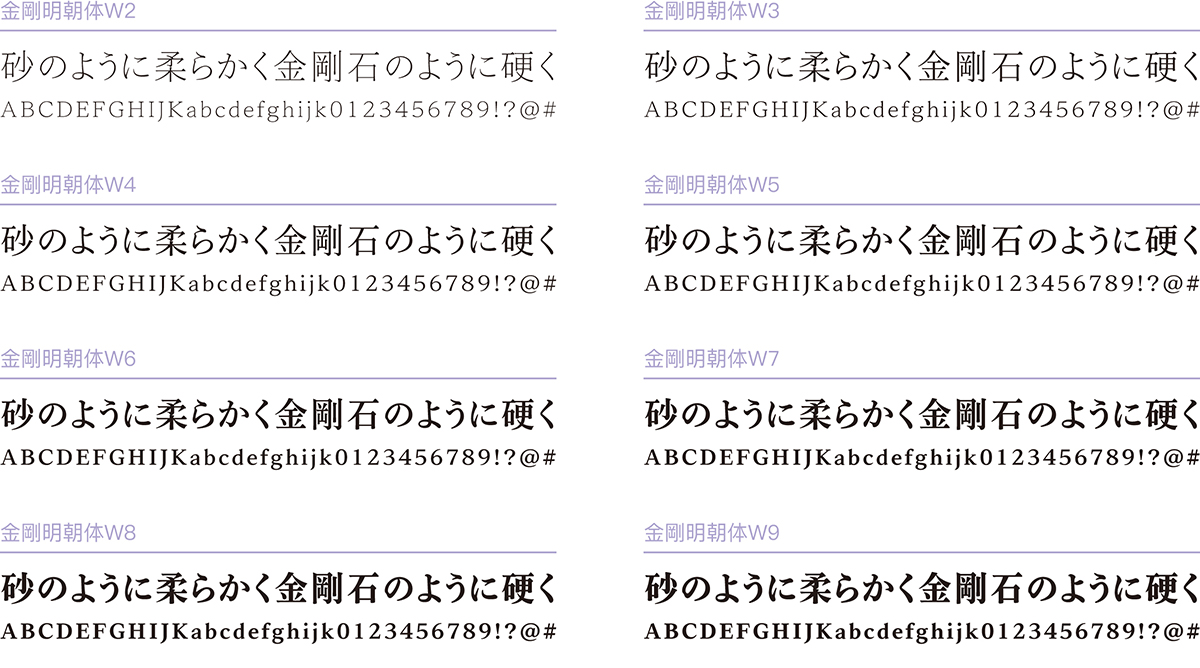
ダイナコムウェアは、ダイナフォント年間ライセンス「DynaSmart V」「DynaSmart 教育機関向けプラン」「DynaSmart 学生版」契約ユーザーに向けて、ダイナフォント30周年となる2023年という節目の年に誕生したダイナフォントの新たなる代表書体「金剛明朝体(ルビ:こんごうみんちょうたい)W2/W3/W4/W5/W6/W7/W8/W9」や、ダイナコムウェアフラッグシップフォントである「金剛黒体」のラテン語およびベトナム語の新ウエイトとして「金剛黒体 多言語【ラテン語・ベトナム語】Bold/Extrabold/Ultrabold/Black/Extrablack/Ultrablack」など、合計48書体を2023年4月18日(火)より提供したことを発表した。
その他、ゲーム作品や映像で多くの採用事例を持つ人気書体「綜藝体(ルビ:そうげいたい)W5/W7/W9」や江戸時代の芝居の看板や番付などに使用されたうねりのある手書き文字を元に開発した書体「勘亭流(ルビ:かんていりゅう)W6/W9/W11」のOpenTypeフォントStdN版や、誰にでも読みやすく配慮した美しい文字「UD明朝体(ルビ:ユーディみんちょうたい)W2/W3/W4/W5/W6/W7」のTrueTypeフォント版も追加収録されている。
【DynaSmart V2023年4月提供書体】柔剛競演によるダイナフォント2023年新明朝体「金剛明朝体(こんごうみんちょうたい)」
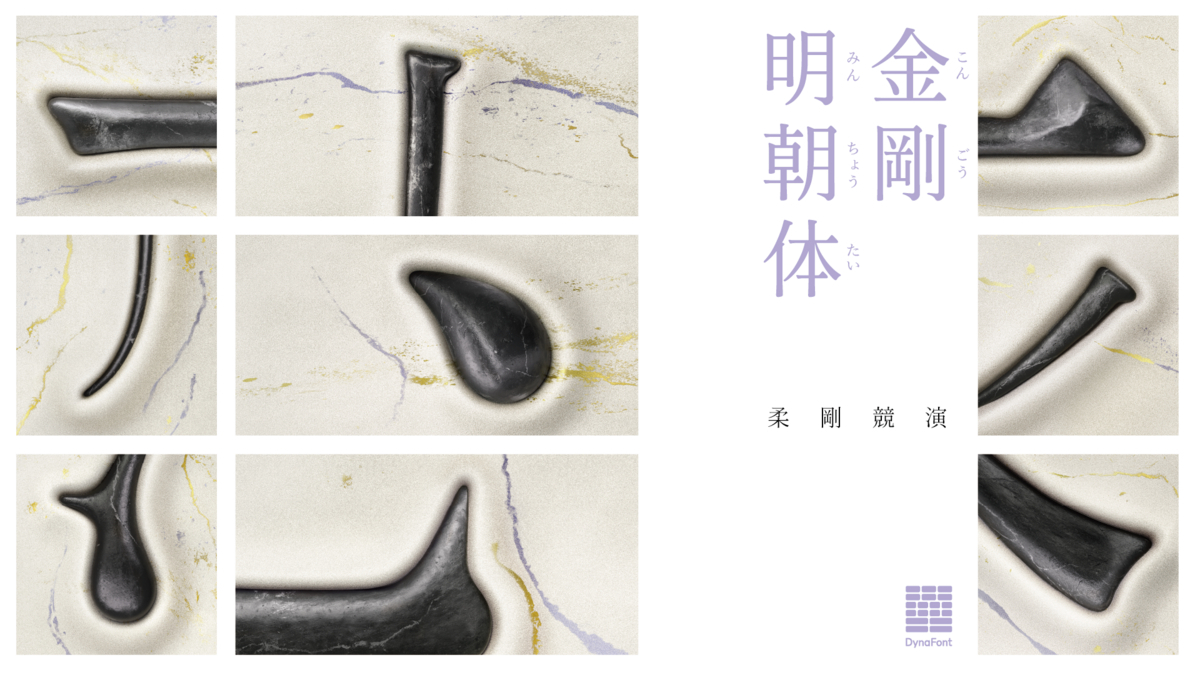
「金剛明朝体」は、彫刻の鋭敏さを和らげて書道の人間味あふれる気品を備えることで、視覚的にも温かくやさしい印象を与えた明朝体となる。
小さめなふところで古典的な雰囲気の佇まいを醸しつつも、横画を太くして角に丸みを持たせることでデジタルにおける卓越した可読性も実現した。古典的で人間味のある美しさを備えながらもデジタルデバイスにも対応しており、まさに新世代の明朝体と言えるだろう。
W2~W9までの8種類のウエイトで展開しており、キャプションから本文、見出しといった小さなサイズでの使用から大きなサイズの使用まで、様々なニーズに対応できる。
ダイヤモンドの王様と呼ばれるカーボネードのような強靭さと繊細さを保ちながらも優しい印象も備えており、紙とデジタル双方において、デザインに彩りや洗練さをもたらしている。
金剛明朝体とその他の明朝体の比較から、組み見本、活用例に至るまで、砂のように柔らかく金剛石のように硬い柔剛競演による新時代の明朝体である「金剛黒体」のその魅力を、余すところなくお伝えした特別なサイトになっている。
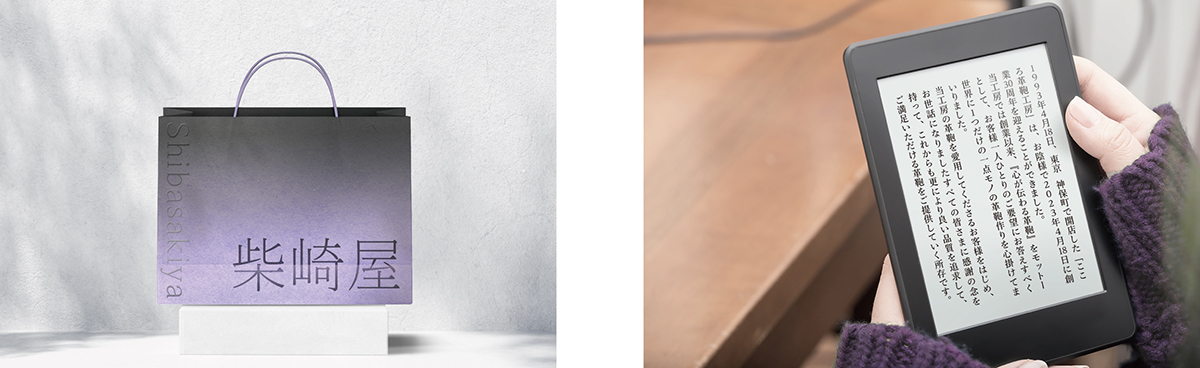
【DynaSmart V2023年4月提供書体】新6ウエイトを追加「金剛黒体 ラテン語Bold 6ウエイト」
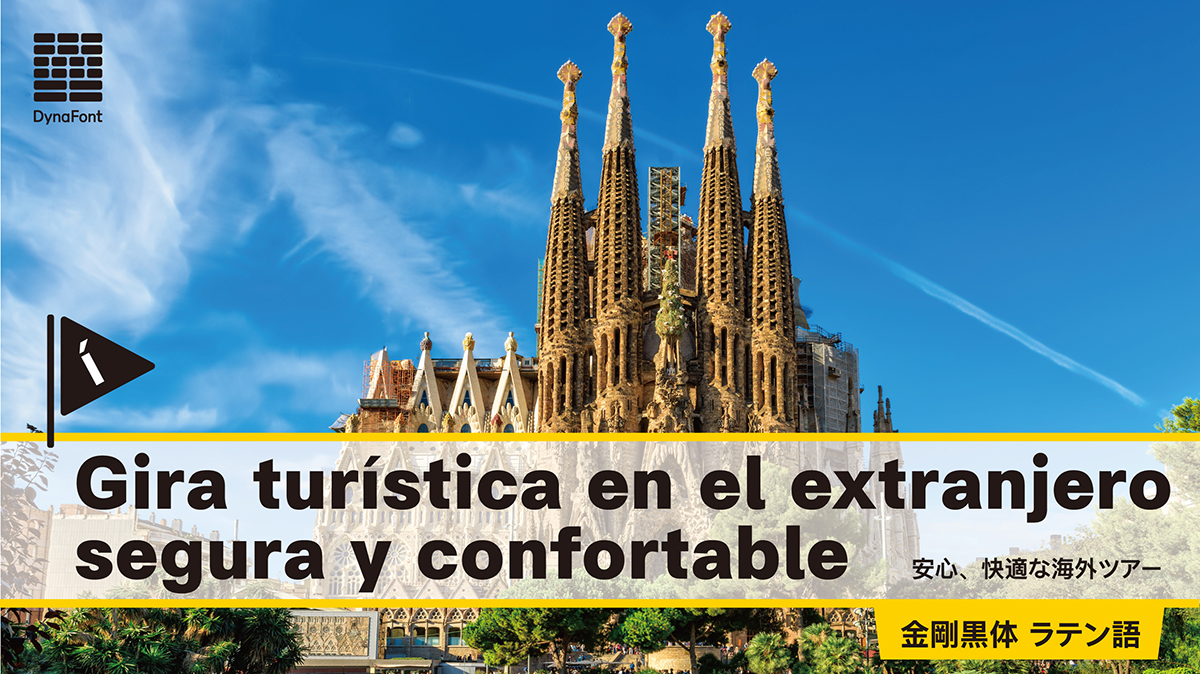
「金剛黒体 ラテン語」は、FIGS(フランス語・イタリア語、ドイツ語、スペイン語)を含むラテンアルファベット137言語の多言語書体となる。
シンプルでモダンなスタイルを軸に、全体的にすっきりと洗練されたデザインが特長。
先行リリースした6ウエイトに、それぞれの太さに合わせて最適化したBold、Extrabold、Ultrabold、Black、Extrablack、Ultrablackの6ウエイトを新たに追加して、拡充した合計12ウエイトで展開。
【DynaSmart V2023年4月提供書体】新6ウエイトを追加「金剛黒体 ベトナム語Bold 6ウエイト」
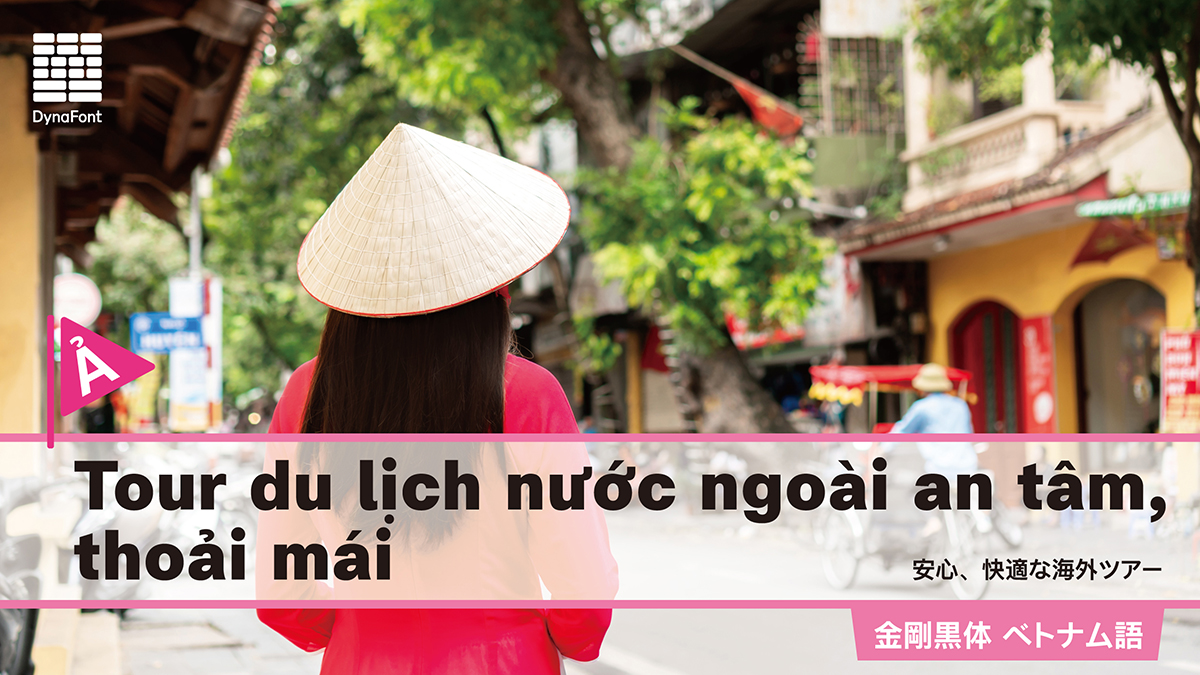
「金剛黒体 ベトナム語」では、ラテン語から派生した現代ベトナム語を採用しており、ラテン語のカーニングで字間のアキを最適化している。
また、表音記号の線を細くして文字とのアキを調整しており、サイズの小さな文字でも読みやすくなるように配慮した。
先行リリースした6ウエイトに、それぞれの太さに合わせて最適化したBold、Extrabold、Ultrabold、Black、Extrablack、Ultrablackの6ウエイトを新たに追加して、拡充した合計12ウエイトで展開。
全ての人に読みやすく配慮した美しい文字「UD明朝体」
「UD明朝体」は、ユニバーサルデザイン(UD)をコンセプトに視認性・可読性の向上させることで、高齢者や弱視(ロービジョン)の方々を含めてすべての人に読みやすいように配慮しつつも美しさも追求した明朝体。
通常の明朝体に比べて、文字のふところを広げ、横画を太く調整、収筆部分には丸みを持たせるなど余計な装飾を省きシンプルにすることで、かすれにくく、どのような場面で文字を見る際にも正確に視認できるように設計した。
また、ユニバーサルデザイン(UD)の機能性だけではなく、快適で自然な読み心地を提供するために明朝体らしい美しさと人の手で書いた趣を残すことで、人間味と視覚的な美しさに回帰している。
W2/W3/W4/W5/W6/W7までの豊富な6ウエイトで展開しており、ウエイトを使い分けることで様々なシーンで幅広く活用できる。